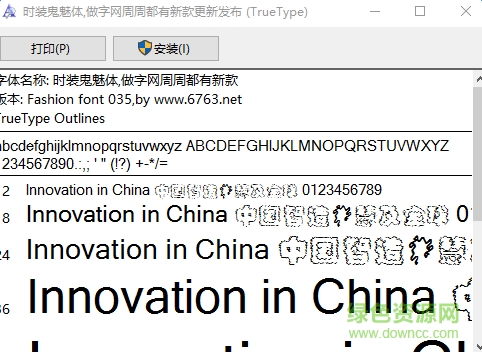
時(shí)裝鬼魅體是時(shí)裝字庫中很有個性的一款電腦字體,這款字體寫出來的字是很特別的,它有幽靈形狀的裝飾物,也正好襯托它的名字,有需要的朋友可以來綠色資源網(wǎng)下載。
時(shí)裝鬼魅體是真的很不錯,不僅字形好看,還有自己獨(dú)特的魅力,這是其他字體都沒有的,而且實(shí)用性也很強(qiáng),可以用于很多方面,歡迎大家來綠色資源網(wǎng)下載。